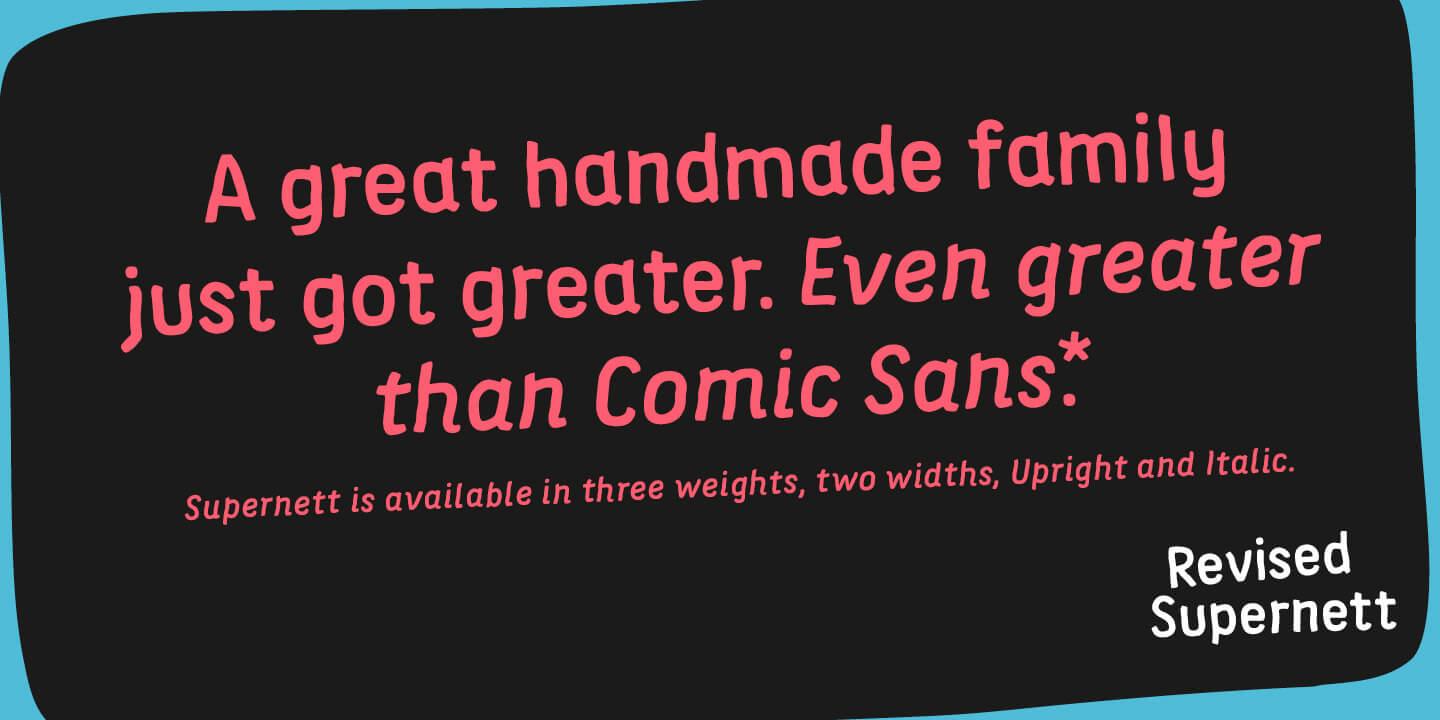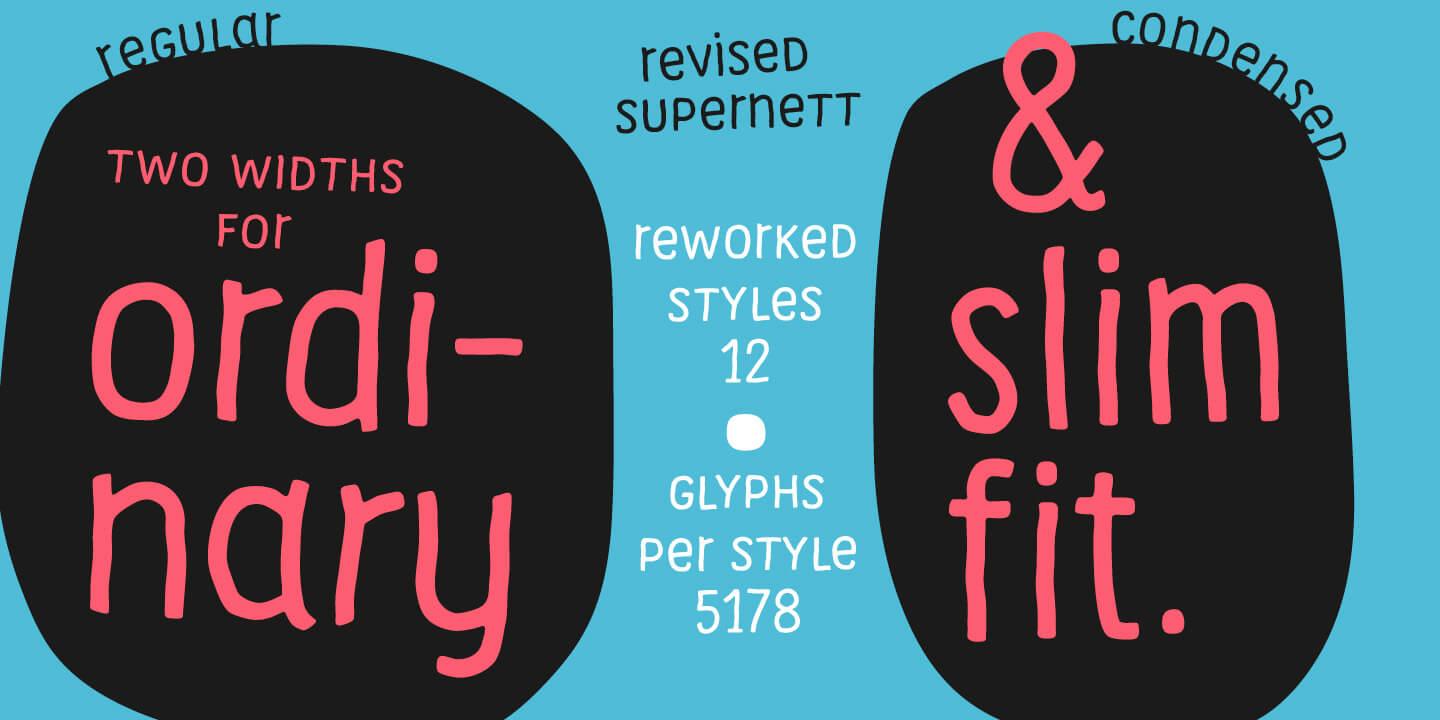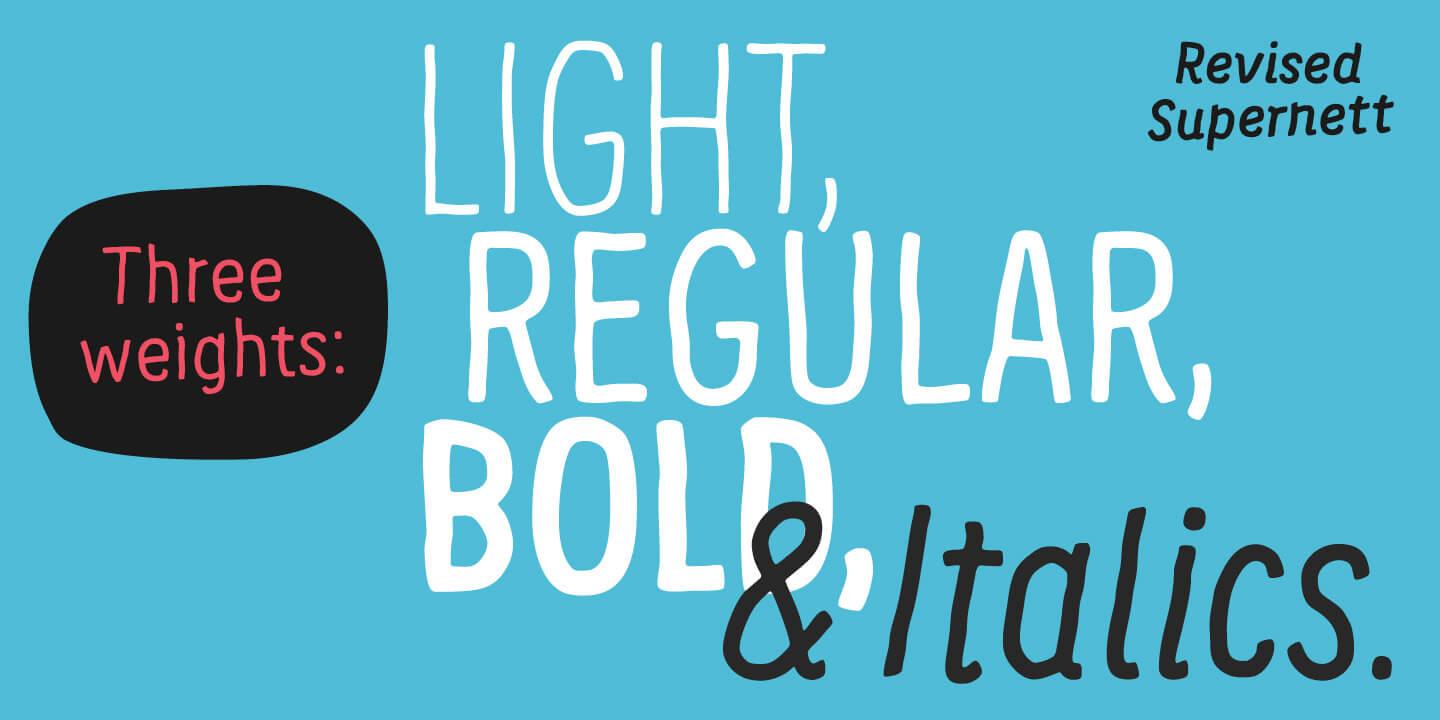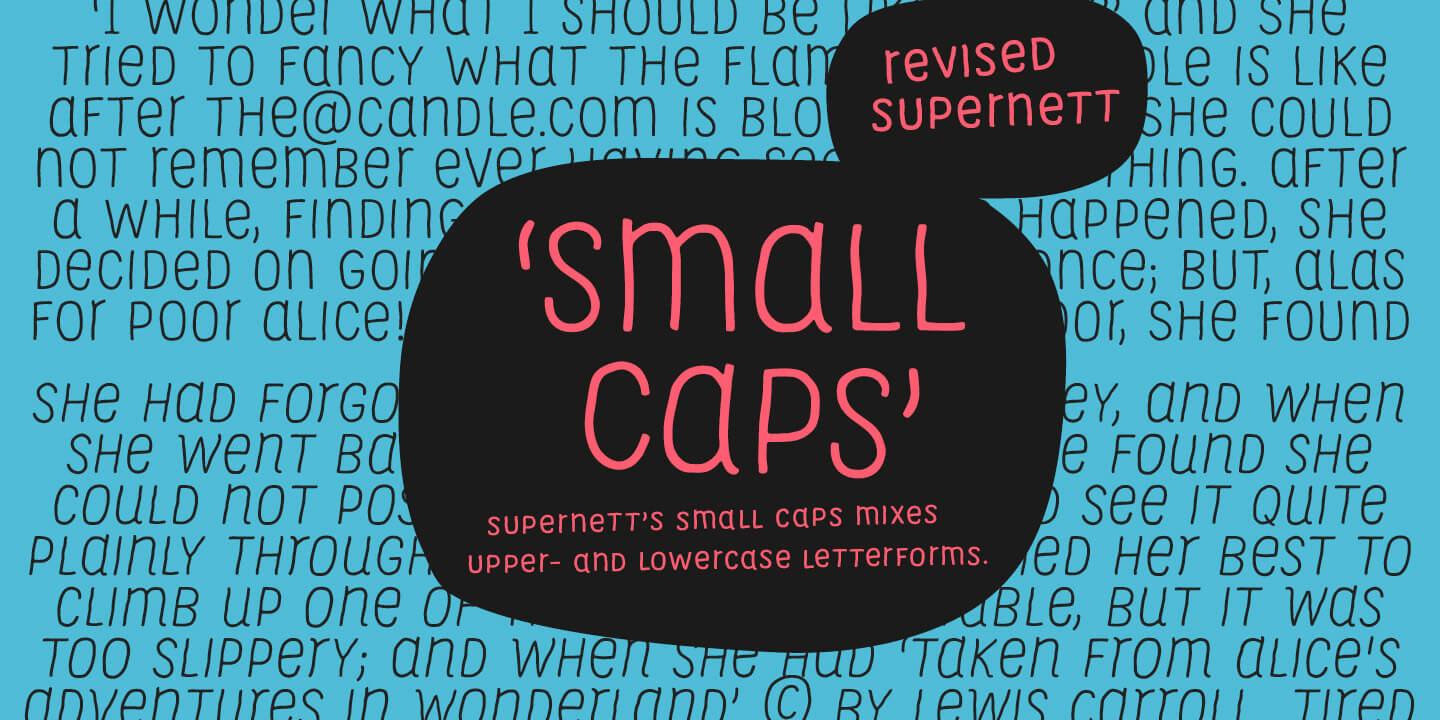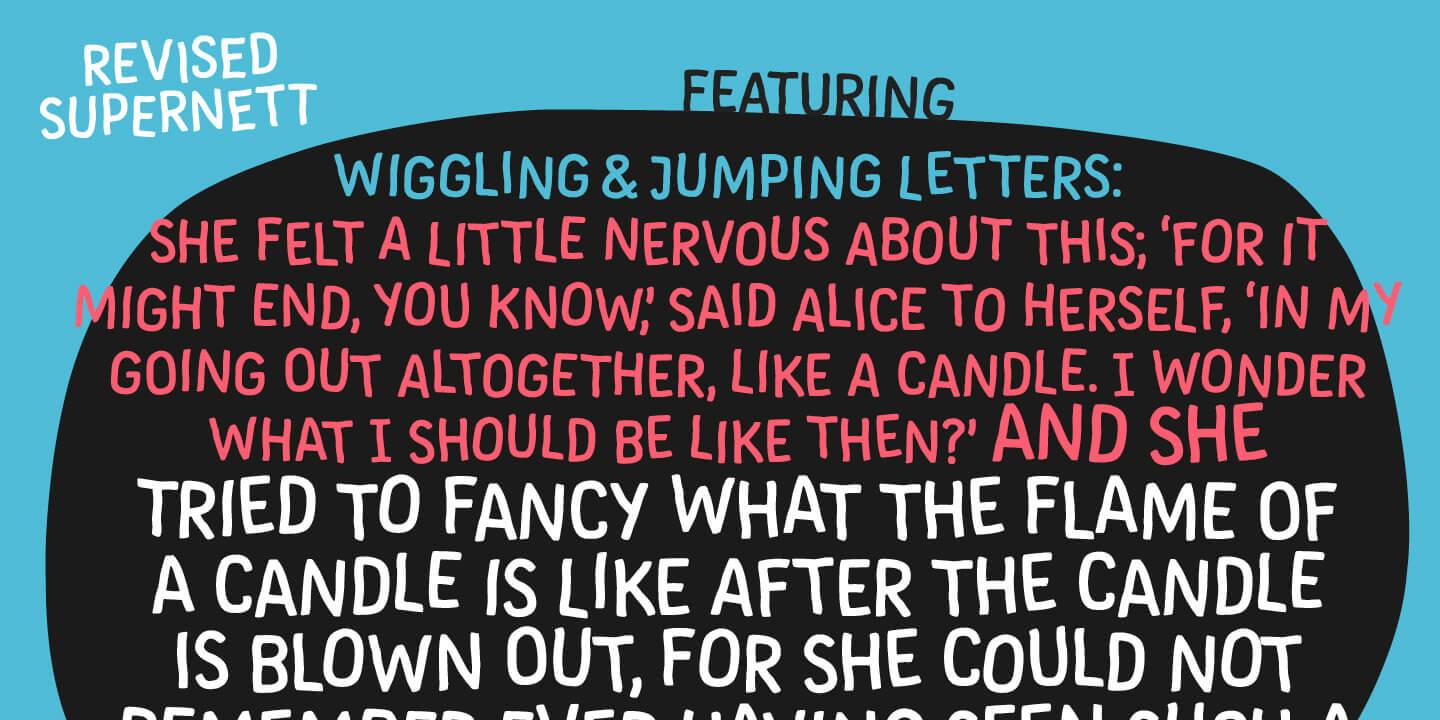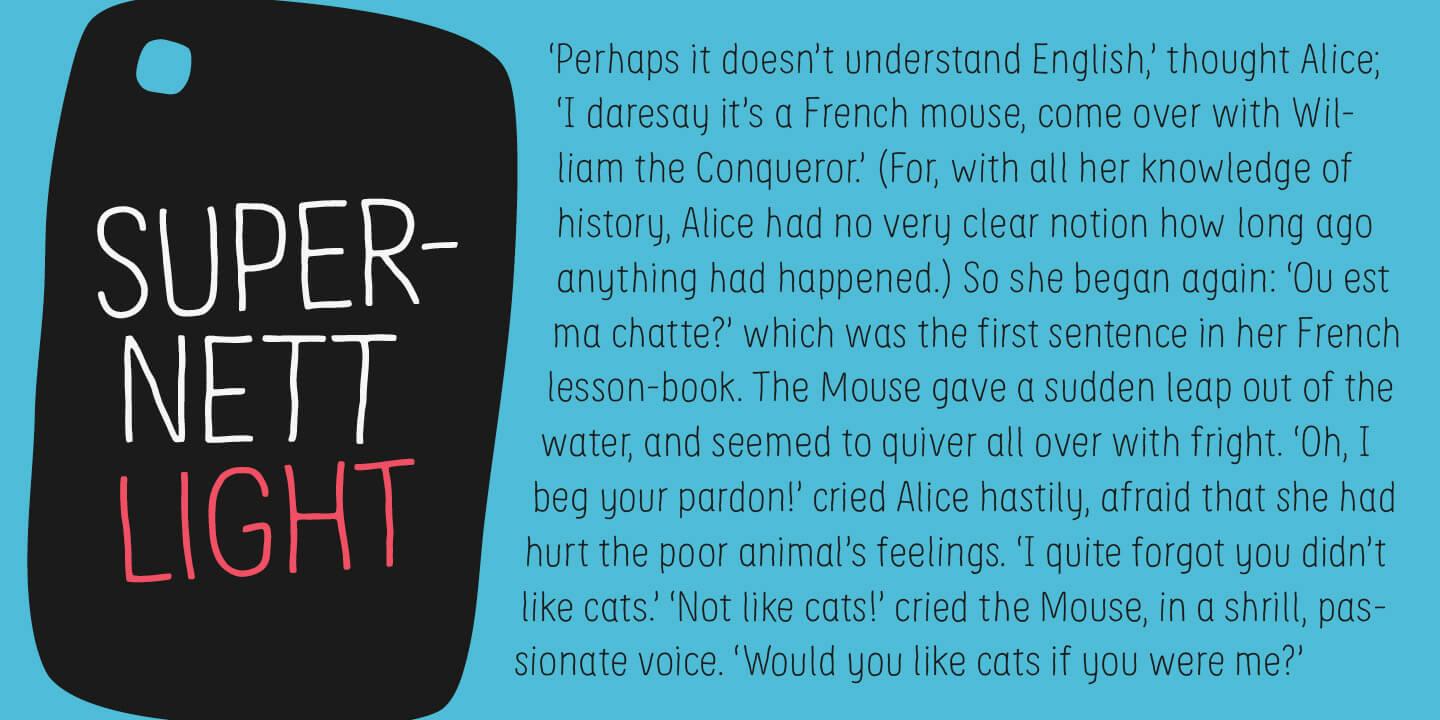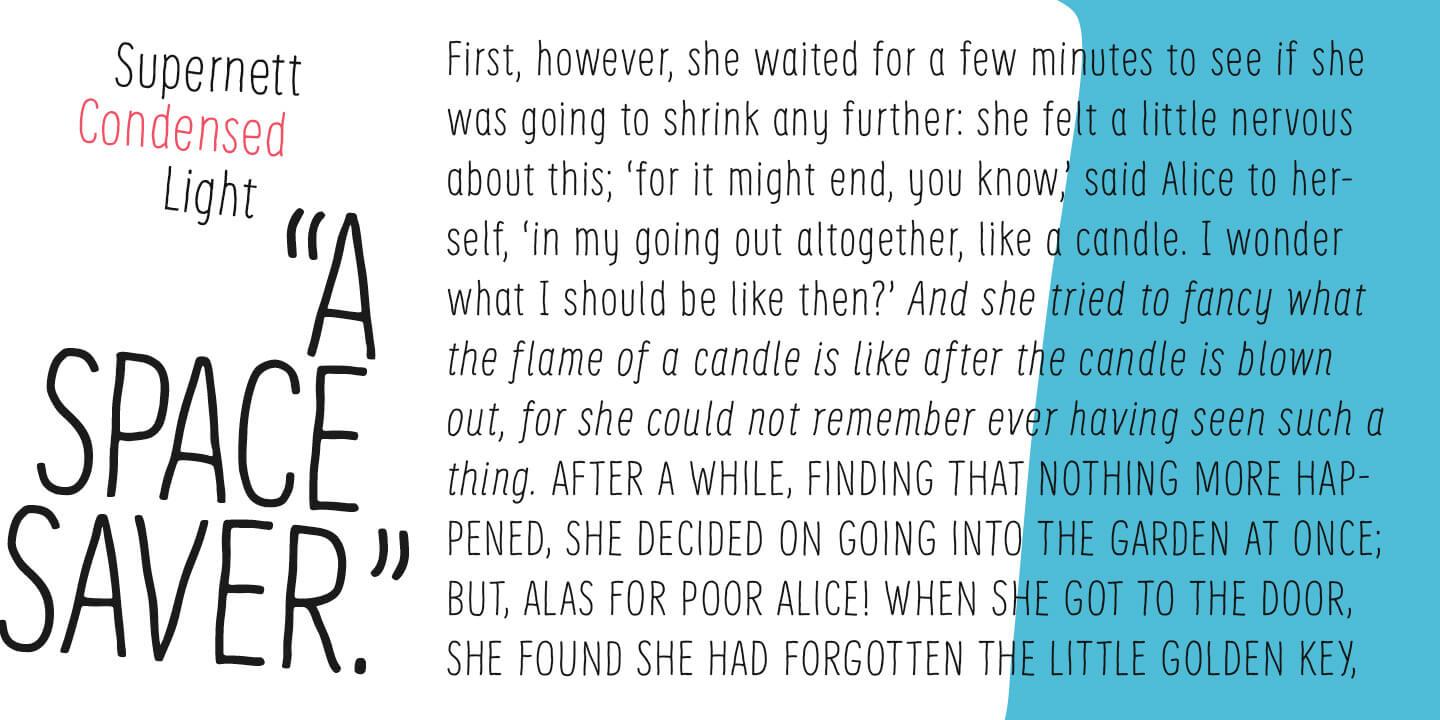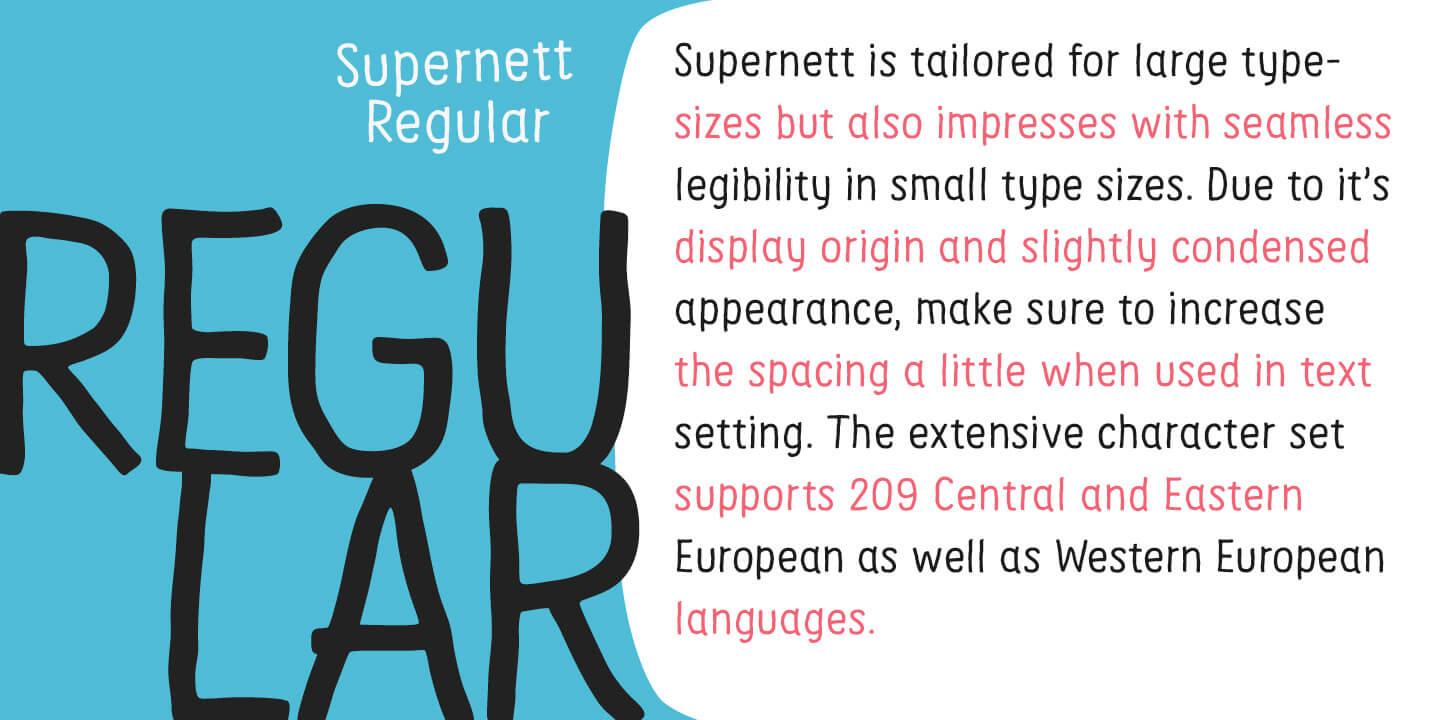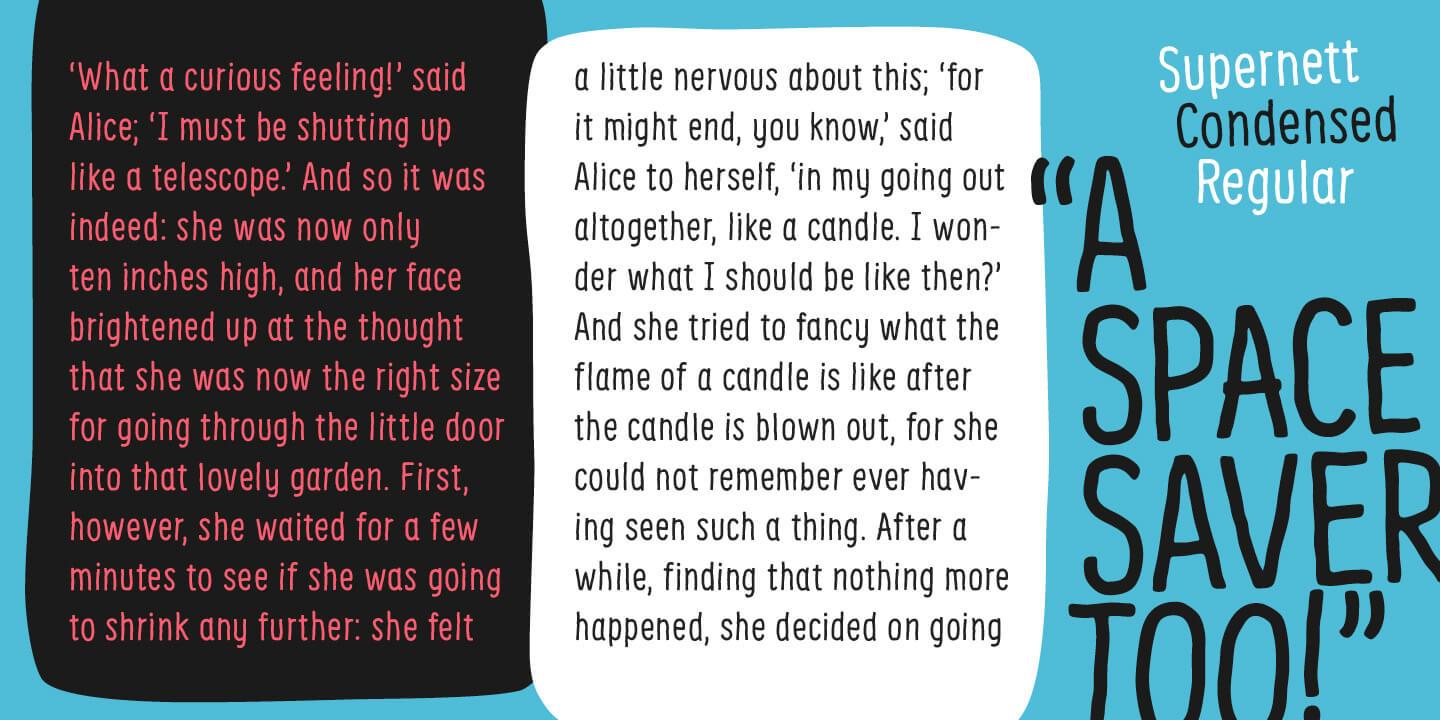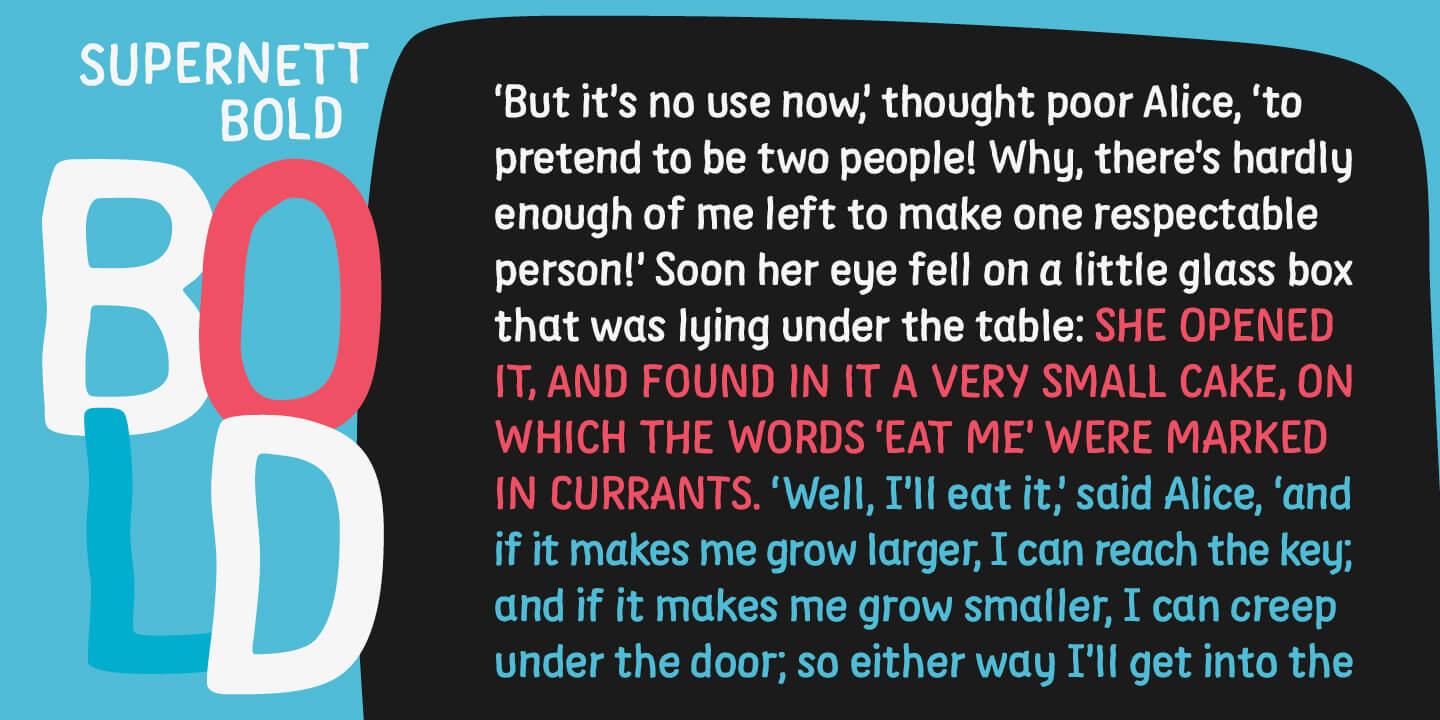
Ich bin Georg Herold-Wildfellner von FaceType und ich möchte euch gerne die neue Schriftfamilie „Supernett“ vorstellen: Die Familie entstand ursprünglich 2013 und wir finden sie seitdem immer wieder auf Packagings oder in Kinderbüchern. Die Nachfrage an der Schrift ist anhaltend gut, also haben wir sie jetzt ausgebaut und erweitert.
Die Familie gibt es jetzt in 3 Stärken, 2 verschiedenen Laufweiten, als Aufrechte und auch als echte Kursive. Das Glyphen-Set unterstützt 209 Sprachen sowie eine Vielzahl an OpenType-Features: ›Automatischer Buchstabenwechsel‹ (alle Buchstaben und Ziffern wurden 3 x gezeichnet), ›Wackelnde Glyphen‹ und ›Zufälliger Grundlinienversatz‹ sind die Key-Features, die den handgemachten Charakter verstärken.
Die Supernett ist als Display-Familie konzipiert und darf groß gesetzt werden. Sie läuft schmal oder sehr schmal und ist für eine Handschrift top ausgebaut: Es gibt Interpunktionen speziell für den Versal-Satz wie auch für die Kapitälchen (die neu dazugekommen sind) und sie unterstützt die OpenType-Features ›Null mit Schrägstrich‹ und ›Brüche‹. Dank der großen x-Höhe (und trotz des handgezeichneten Looks) überzeugt die Supernett mit guter Lesbarkeit im Mengensatz. Ihr organischer, handgemachter Charakter passt zu Kinderbüchern, Packaging und Food.
Supernett wurde von Georg Herold-Wildfellner/FaceType gestaltet.
Jetzt gibt's sie immerhin auch in normaler Laufweite und nicht nur Cn ... ich hab mich immer gefragt, warum man zuerst den Condensed-Schnitt macht  ...
Ein kleiner Tipp: Wollt ihr die Schrift auch ernsthaft für ungarische Anwendungen anbieten, müssten die Diakritika bei Ő, Ű, ő und ű noch angepasst werden.
Die haben im Ungarischen nämlich immer dieselbe Neigung wie die Diakritika der anderen langen Vokale, also Á, É, Í, Ó, Ú und á, é, í, ó, ú. Dieses eherne Gesetz der ungarischen Typografie gilt auch für Hand- und handschriftlich anmutende Schriften.
Wollt ihr diesen Schönheitsfehler zu beheben, habt ihr zwei Möglichkeiten:
1. Die einfache: gebt den Doppelakuts einfach denselben Neigungswinkel wie den einfachen.
2. Die etwas komplexere, aber leicht schönere: passt sie Neigungswinkel der einfachen Akuts in ungarischsprachigen Einsätzen (also wenn locl(hu) aktiv ist) dem der doppelten an. Das wäre deswegen ein bisschen schöner, weil die meisten ungarischen Schreiber dazu tendieren, in Handschriften Akuts und Doppelakuts sehr steil (wenn nicht ganz und gar senkrecht) zu setzen.
Allerdings wären beide Ansätze voll akzeptabel.
Habe die Version v1.096 mit der 1.052 aktualisiert und soeben festgestellt das die neuere Version viel weiter läuft (condensed). Das ist ziemlich blöd, weil es mir meine Zeilen im Dokument nun komplett umbricht. In diesem Fall muss ich leider wieder zurück zu alten Version wechseln. 😖